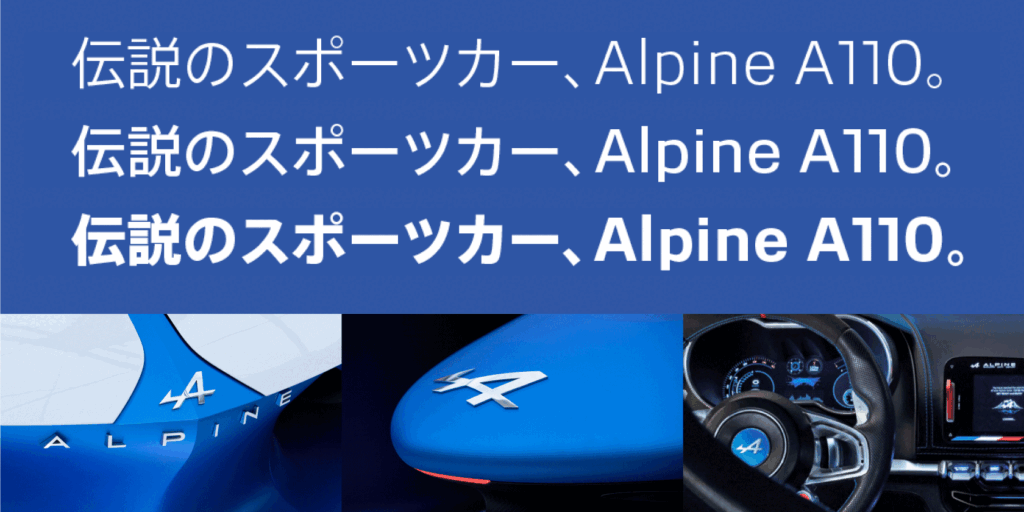
今回の記事では、フィットフォントの技術を利用して書体開発・提供を行なった事例を紹介します。1つめは、クライアントから提供された欧文フォントに合わせてタイププロジェクトの和文フォントを調整した事例です。
フランスの自動車メーカー AlpineにはProduction Typeによって開発された「Alpine Ascension」 という欧文コーポレートフォントがありました。彼らの日本語対応のため、Alpine Ascensionファミリーに加わる和文フォントとして、タイププロジェクトはAXISフォントを元にカスタマイズした和文書体 「Alpine AXIS」を提供しました。「Alpine AXIS」のウェイトはフィットフォントの技術によってAlpine Ascensionファミリーのウェイトに合わせて調整されました。